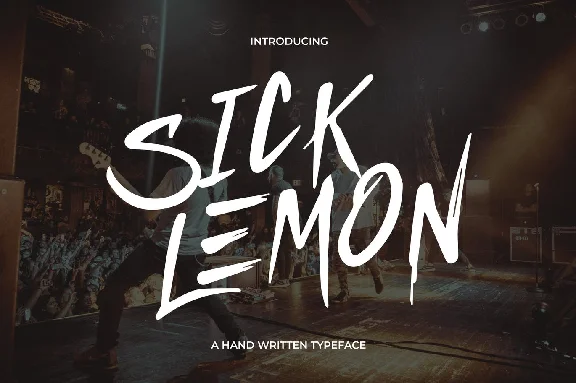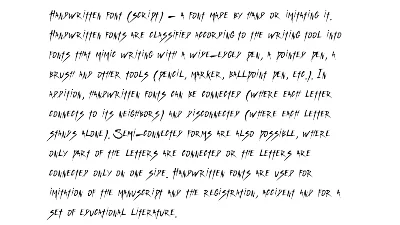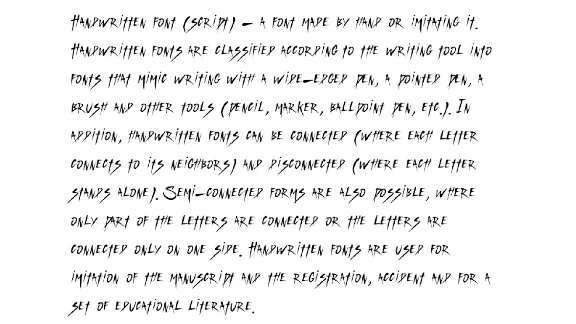
Шрифт SICK LEMON - ручной письменный тип
Sick Lemon - это случайный шрифт с естественным штрихом, он состоит из прописных, строчных букв, цифр и знаков препинания. Этот шрифт будет идеальным выбором для различных дизайнов и произведений искусства, таких как пост в социальных сетях, тип бренда, плакаты, товары, упаковка, заголовки, товары, футболки и многое другое.